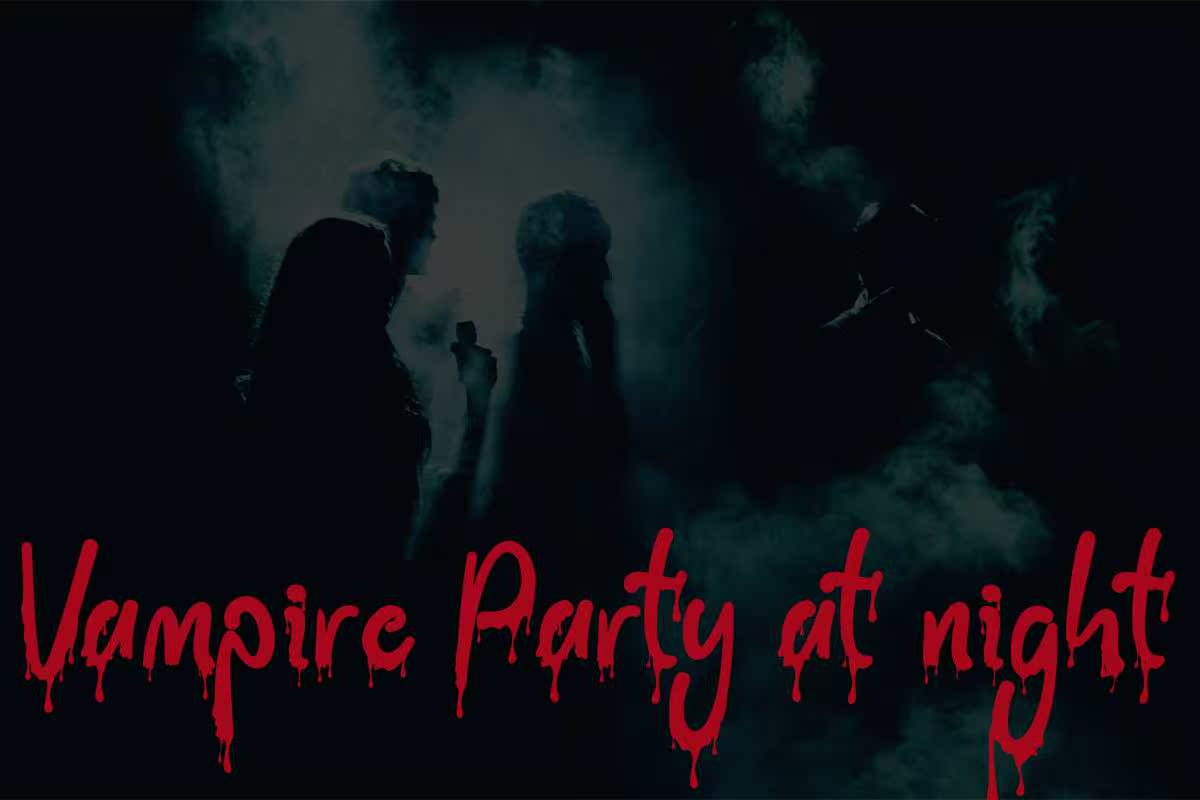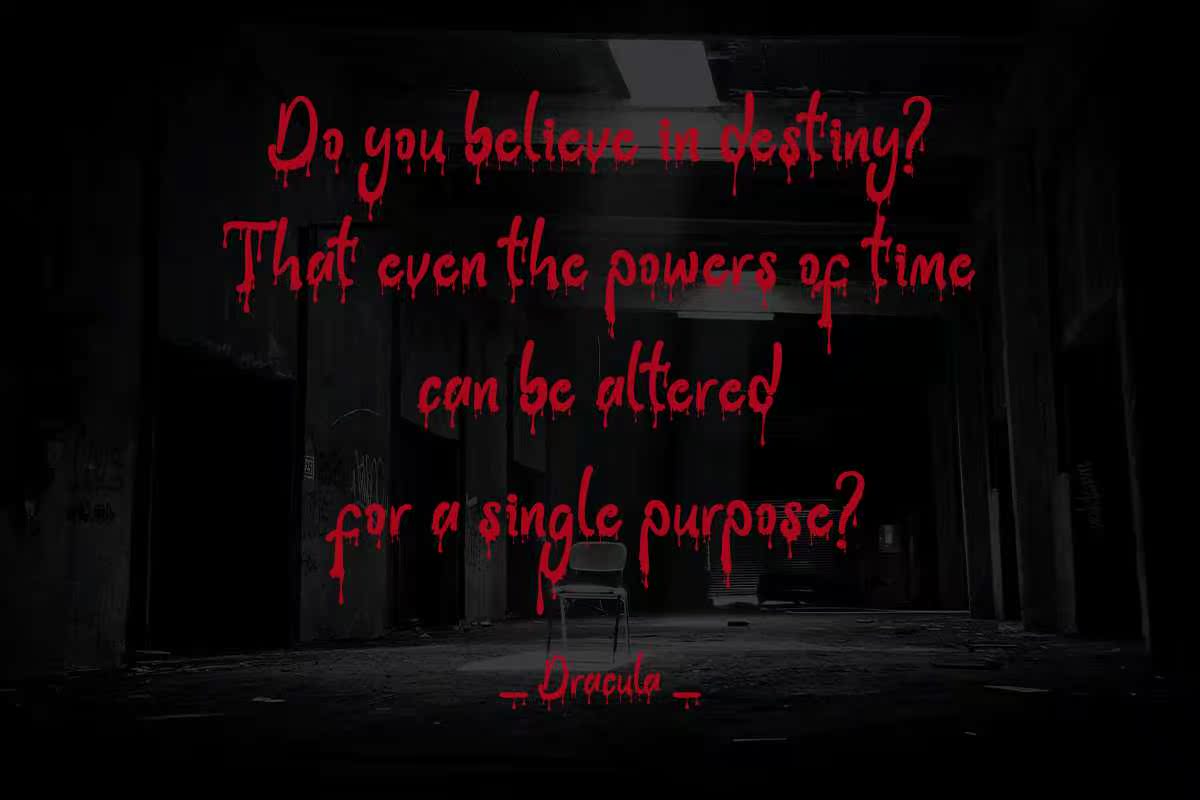
这款香水被命名为“万圣节派对”。这款香水是有意为即将到来的万圣节派对添加一些特别的东西。这款“万圣节派对”香水之所以特别,是因为它有血染。这款香水是为你的万圣节派对添加特别和神秘的元素的完美之选。除了万圣节派对,这款香水还可以为你的万圣节派对添加一些特别的东西,书名或其他内容设置为书名水渠,还有其他的。这款香水被命名为“万圣节派对”。这款香水是有意为即将到来的万圣节派对添加一些特别的东西。这款“万圣节派对”香水之所以特别,是因为它有血染。这款香水是为你的万圣节派对添加特别和神秘主义的完美之选。除了万圣节派对,这款香水还可以为你的万圣节派对添加一些特别的东西,书名或其他内容包括书名、水渠、文字、神秘故事、神秘故事和神秘故事邀请卡等。